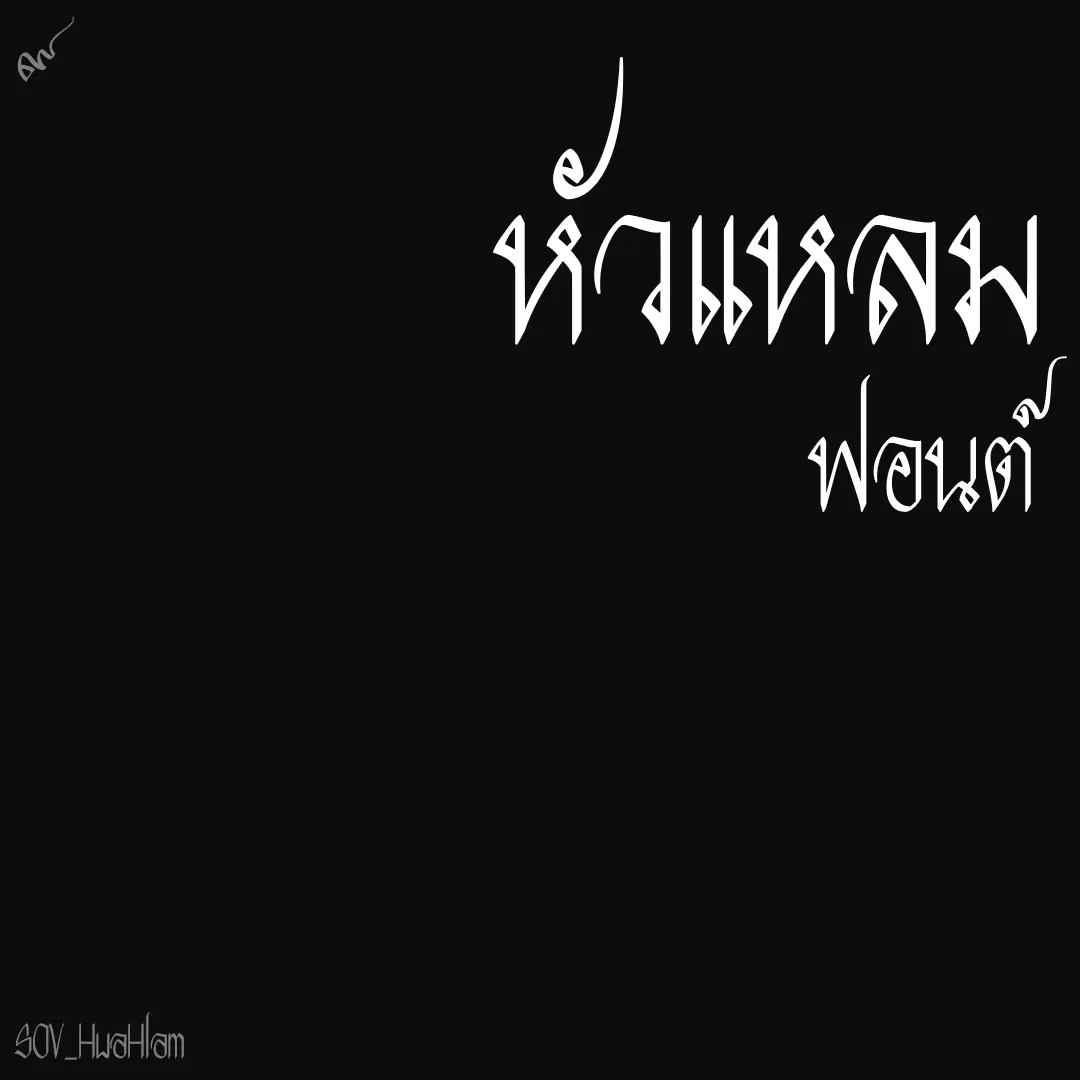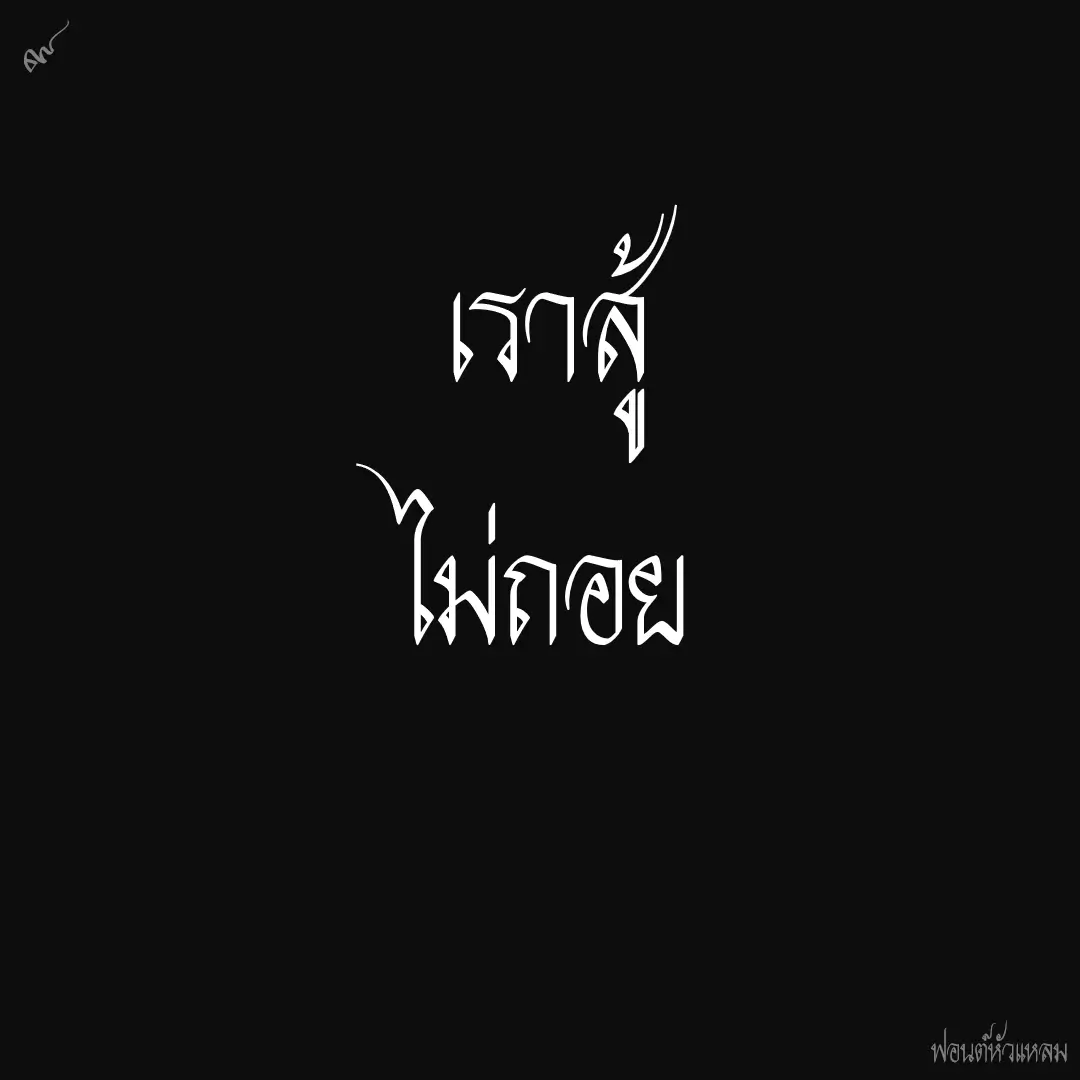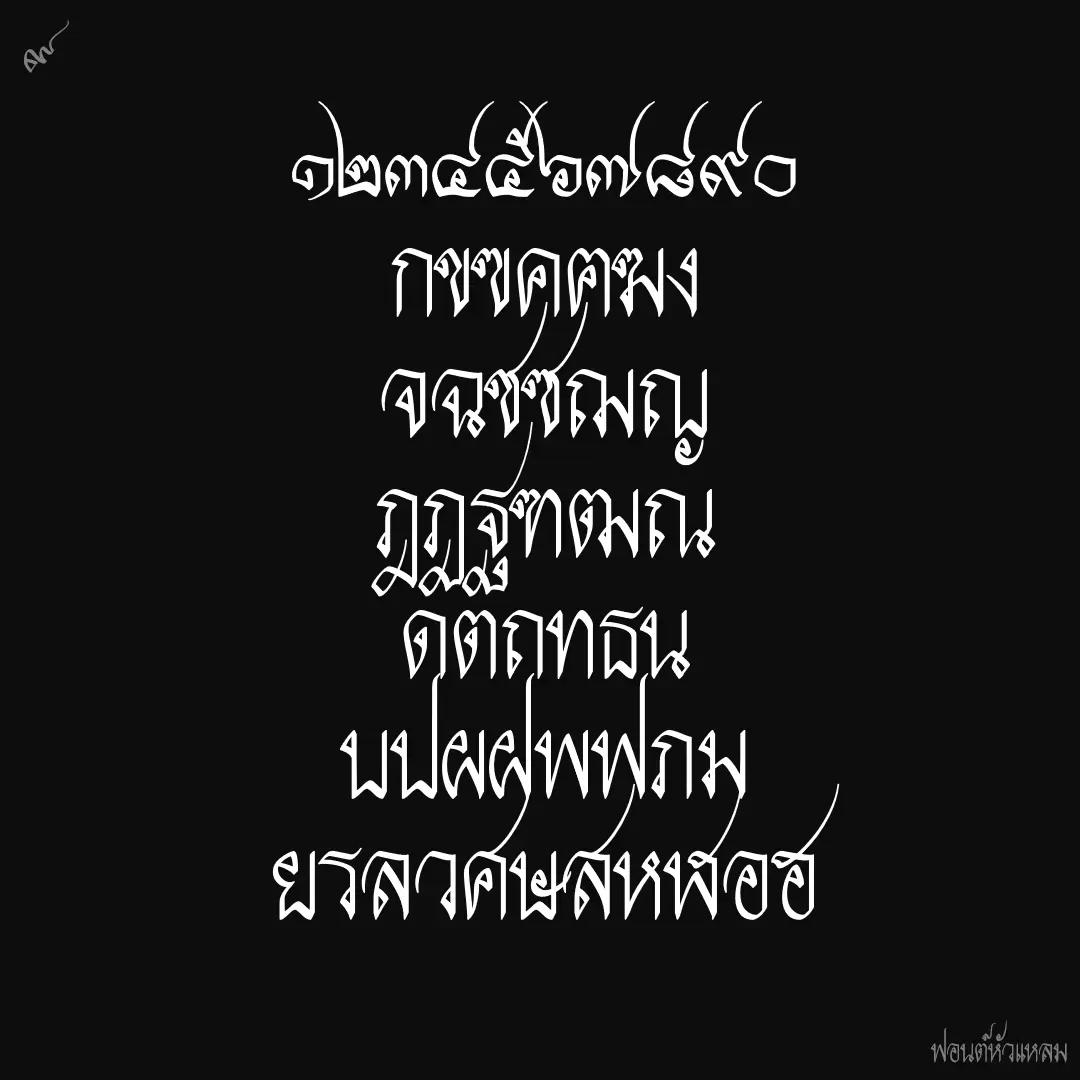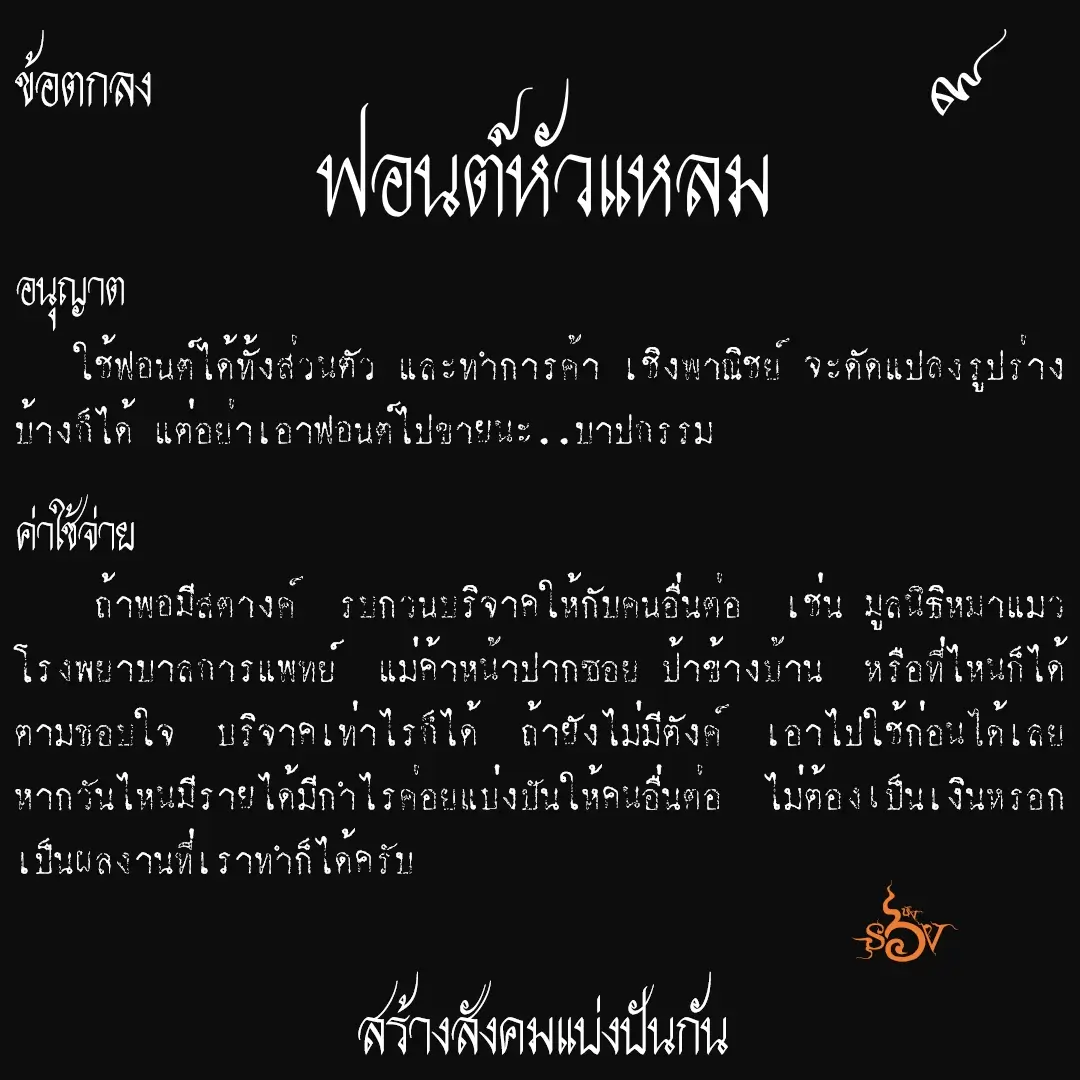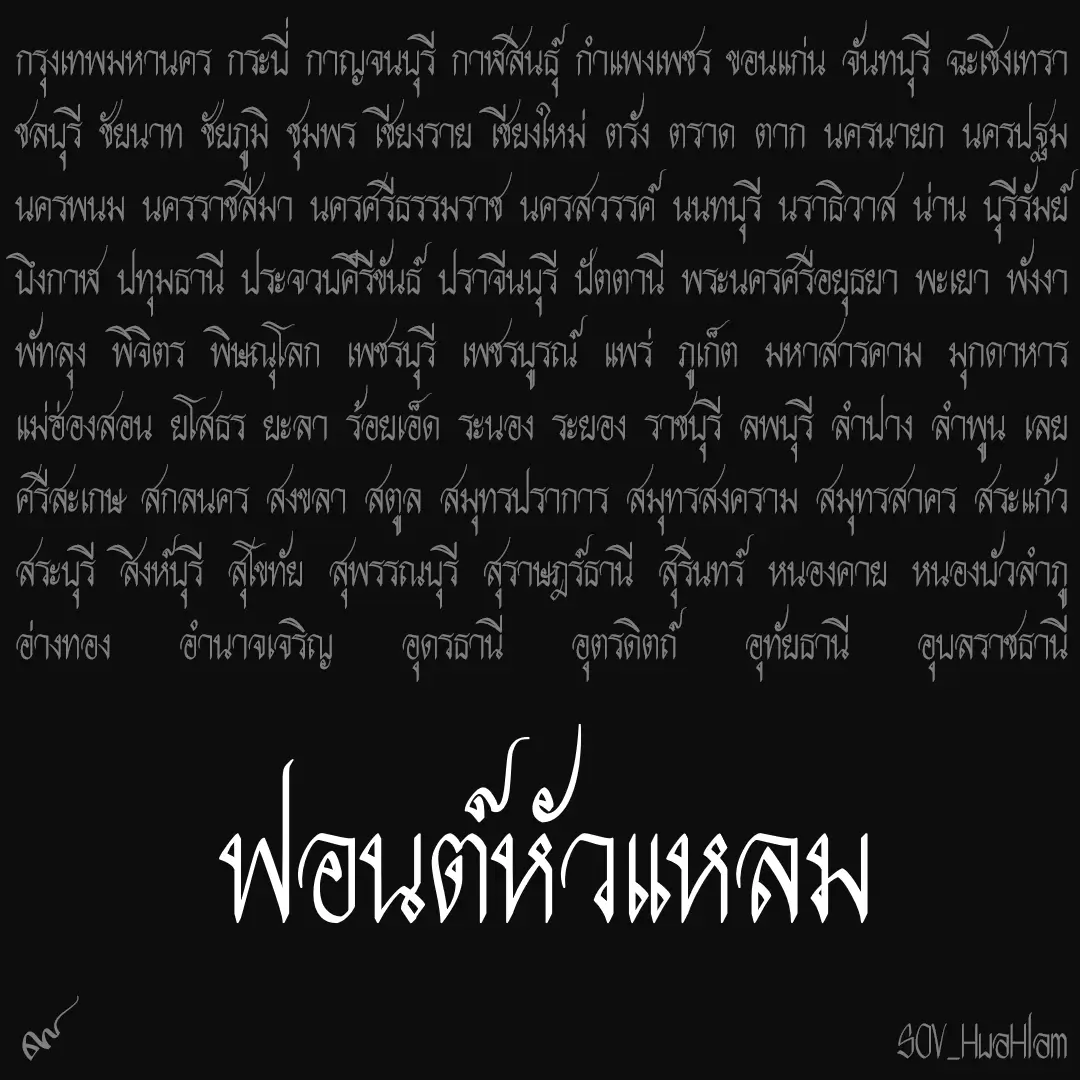
ฟอนต์หัวแหลม ต้นทางจากหลังปกสมุดแจก เมื่อสมัยเป็นเด็ก เห็นหัวแหลมแปลกตาทรงสามเหลี่ยม แต่ก็ยังมีผสมหัวบัวอยู่ จึงปรับให้กลายเป็นหัวแหลมทั้งหมด และเพิ่มตัวละตินให้เข้าชุด
เบื้องหลังการออกแบบ : ฟอนต์ หัวแหลม
หัวแหลม (SOV_HuaHlam)